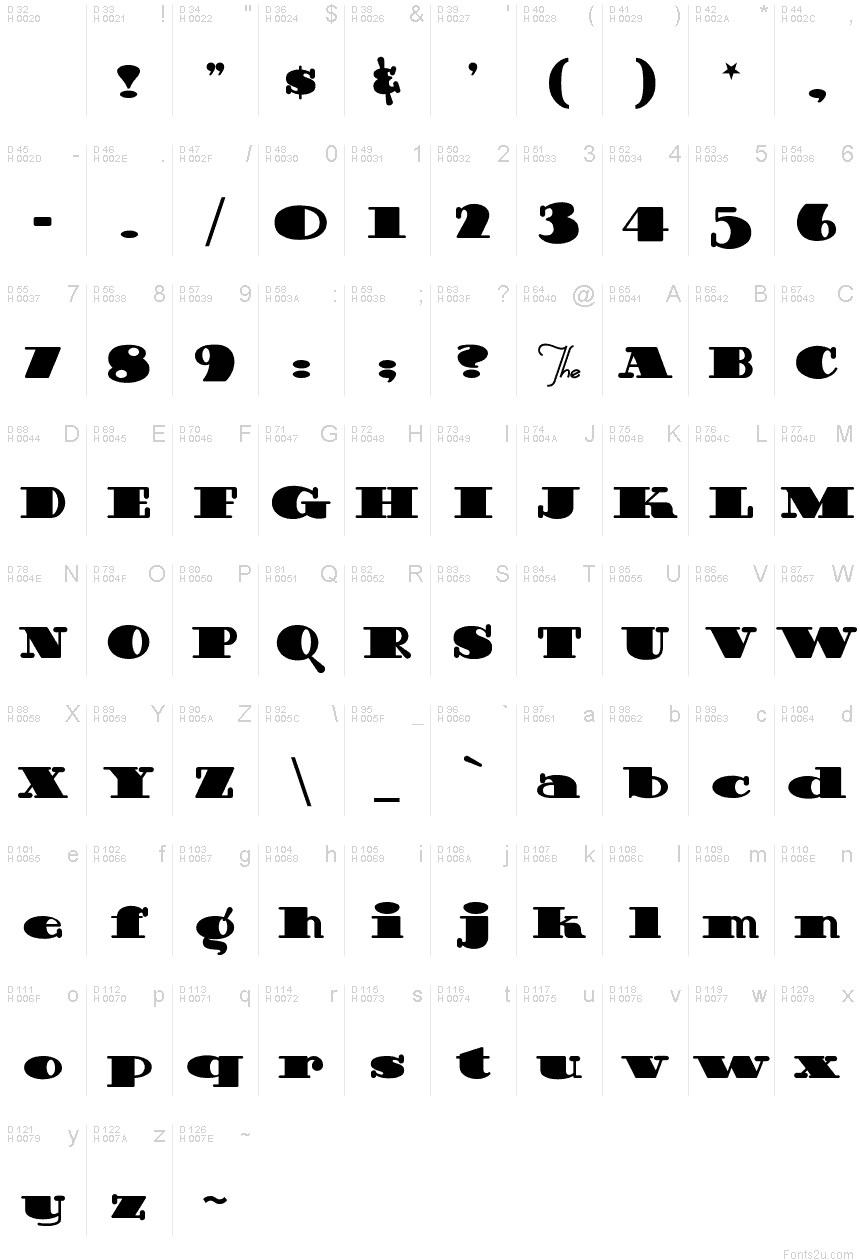
Guinness Extra Stout od Nicka Curtisa to darmowy, retro krój displayowy, który na stronie układa się niczym gęsty kleks atramentu. Jego przysadziste, ultra-pogrubione litery są ciężkie i gładkie, a miękkie krzywizny przeplatają się z blokowymi pionami, wyglądającymi niemal jak odlane z formy. Te solidne i osadzone kształty nadają nagłówkom charakteru szyldu z pubu – są głośne, ciepłe i odrobinę zadziorne, a przy tym wciąż czytelne na pierwszy rzut oka.
Guinness Extra Stout to charyzma starego świata, która natychmiast buduje tożsamość wizualną każdego projektu. Ten darmowy font świetnie sprawdza się na etykietach piw, opakowaniach tradycyjnej żywności, plakatach w stylu vintage, logotypach tawern i kawiarni, ulotkach czy odważnych grafikach na gadżety. Stosuj go w dużych rozmiarach i zestawiaj z prostym krojem bezszeryfowym w tekstach głównych, aby charakterne litery stout mogły błyszczeć, nie przytłaczając przy tym całego układu.